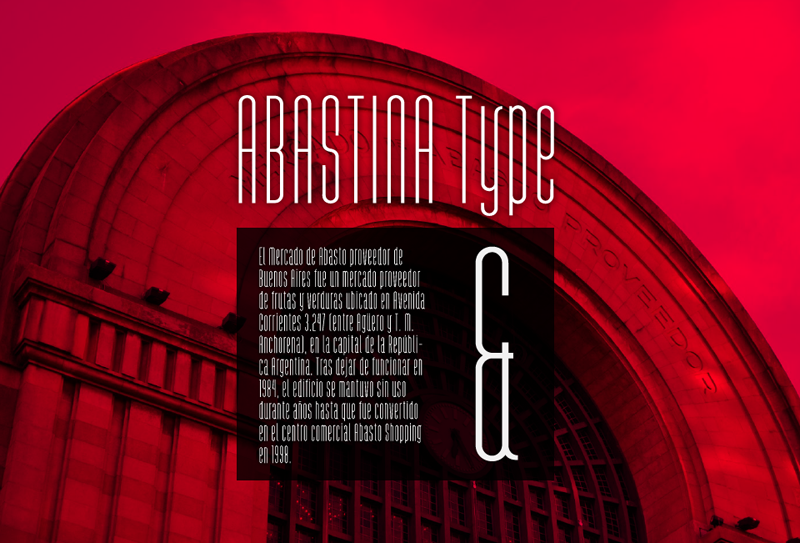
Abastina es una tipografía para títulos y textos cortos. Está basada en la arquitectura del Mercado del Abasto en Buenos Aires Argentina. La tipografía es gratuita para uso no comercial de ser así contactarse con nosotros. |